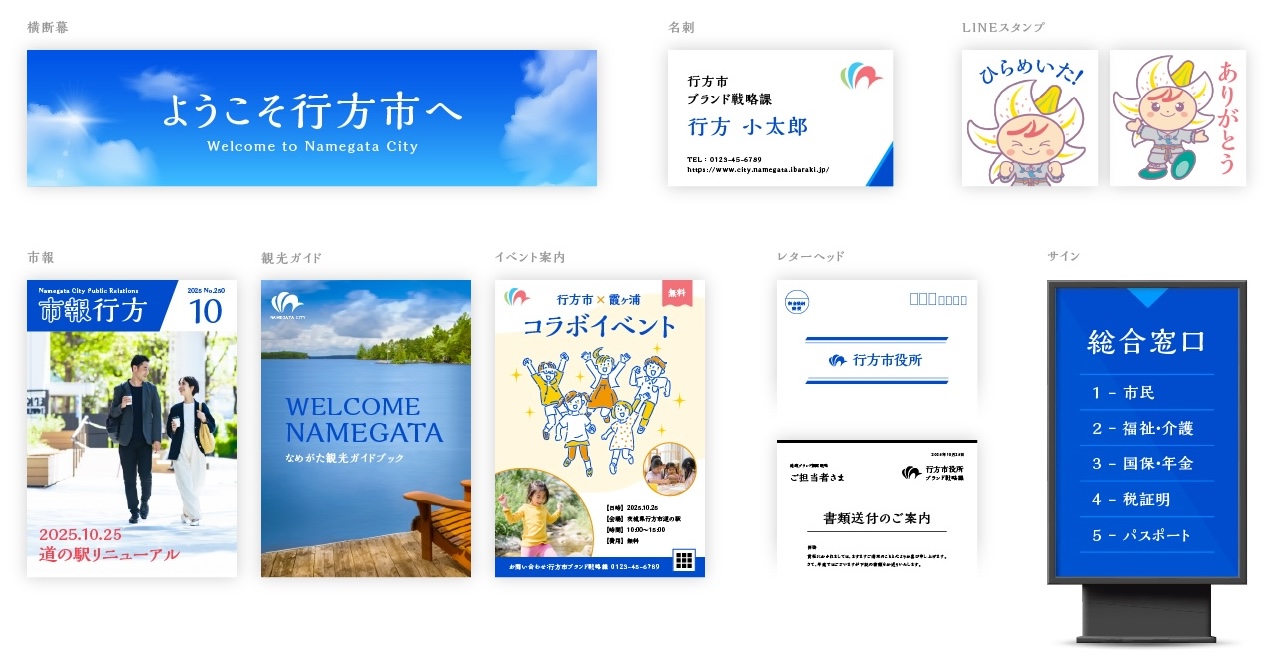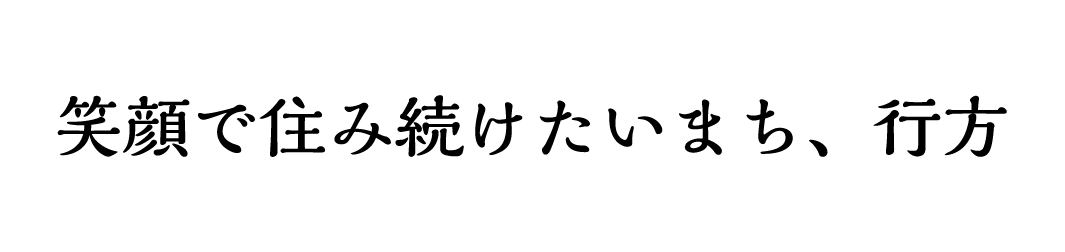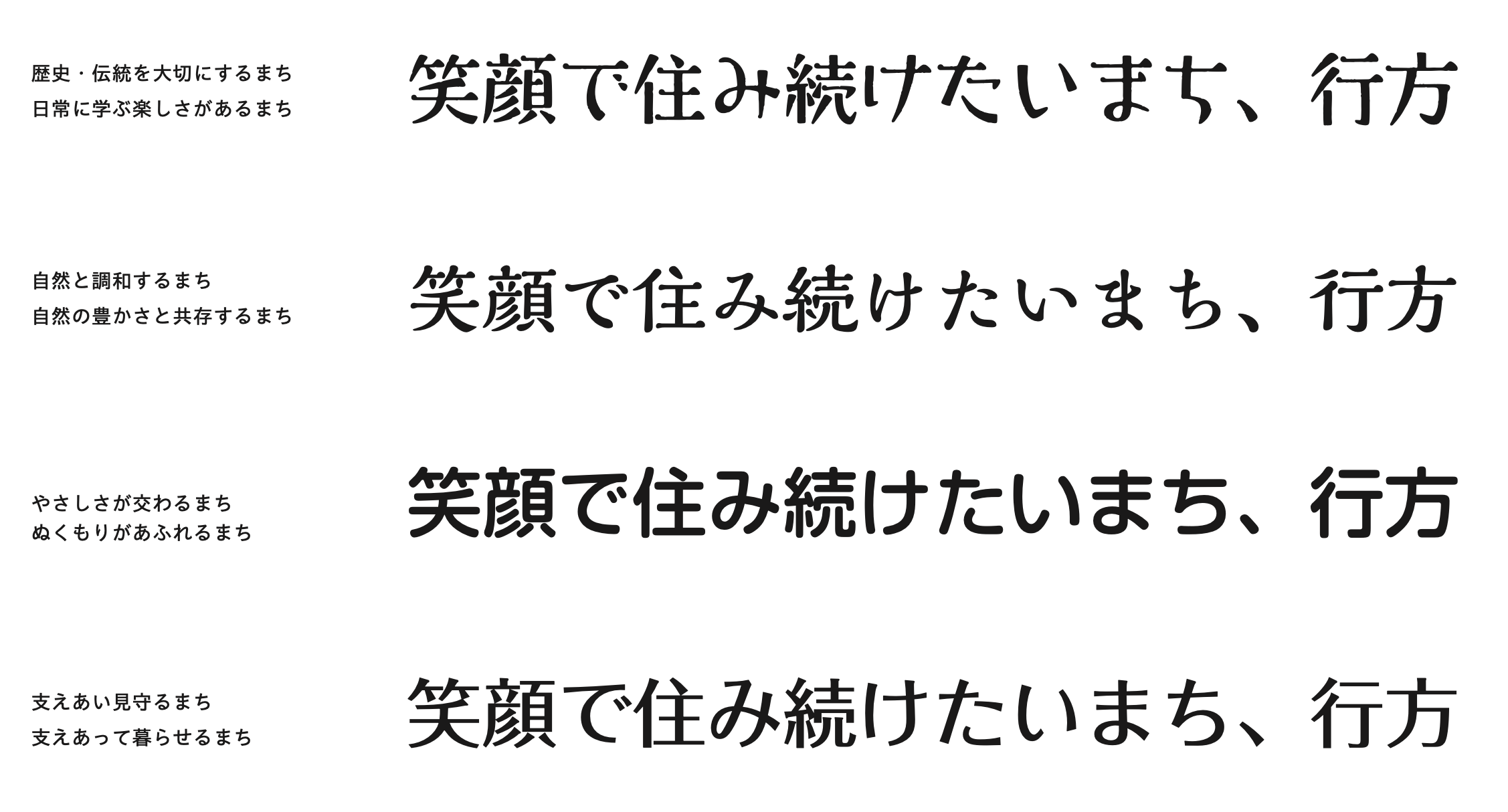
モリサワ 茨城県行方市の制定書体決定に協力〜国内自治体では先駆けとなる地域ブランディングの施策〜
株式会社モリサワ(以下モリサワ)は、茨城県行方市が市制施行20周年を記念して実施する国内自治体としては先進的な取り組みとなる「行方市フォントプロジェクト(行方市制定書体プロジェクト)」に、フォントメーカーとして協力しています。本プロジェクトは、地域ブランディングの一環として、地域の職員や子どもたち自身が「行方市らしさ」を見つめ直し、自分たちが描く未来のまちの姿を反映した制定書体を策定するものです。この度、投票によって「解ミン 宙」が行方市の制定書体に選ばれました。
モリサワは、書体の制定まで行方市の職員の皆さんや住民の皆さんと「行方市らしさ」を一緒に考えてきました。2025年7月に行方市職員を対象としたワークショップを実施し、「行方市らしさはどこにあるのか?」を多角的に検討しながら、観光客や住民に伝えたい印象を抽出しました。その成果をもとに、候補となる4書体を選定しました。
8月には市内の小学生を対象に「もじでつくろう 行方のポストカード」と題したワークショップを開催。子どもたちは市の写真に文字を組み合わせてポストカードを制作し、未来の行方市を思い描きながら候補書体への模擬投票も行いました。さらに中学生による投票を経て、「自然と調和するまち・自然の豊かさと共存するまち」をテーマにした「解ミン 宙」が制定書体に選ばれました。
今回の制定書体は、広報物や名刺などの行政発信に活用され、行方市の独自性を内外へ示すものです。自治体のDNAを書体デザインと関連付けて、市の職員や住民自ら書体を選定・制定し共通の書体を用いることは、一体感の醸成やインナーブランディングの推進につながると期待しています。